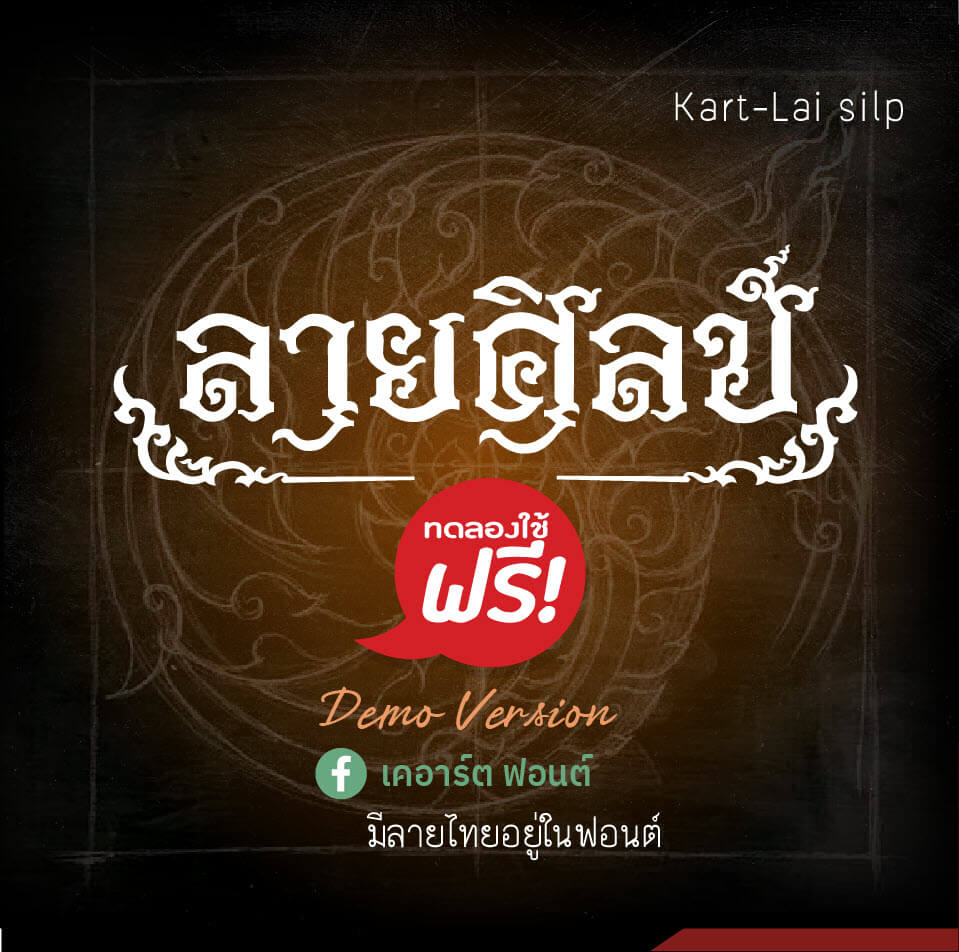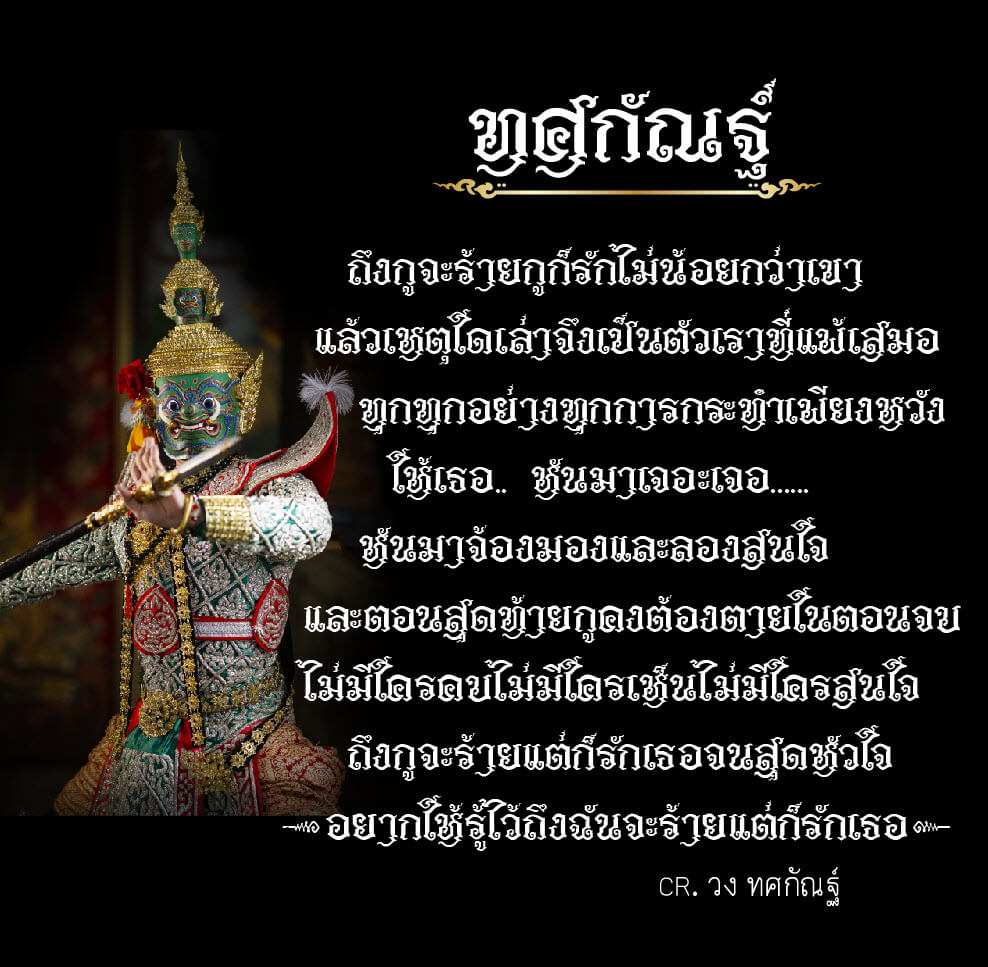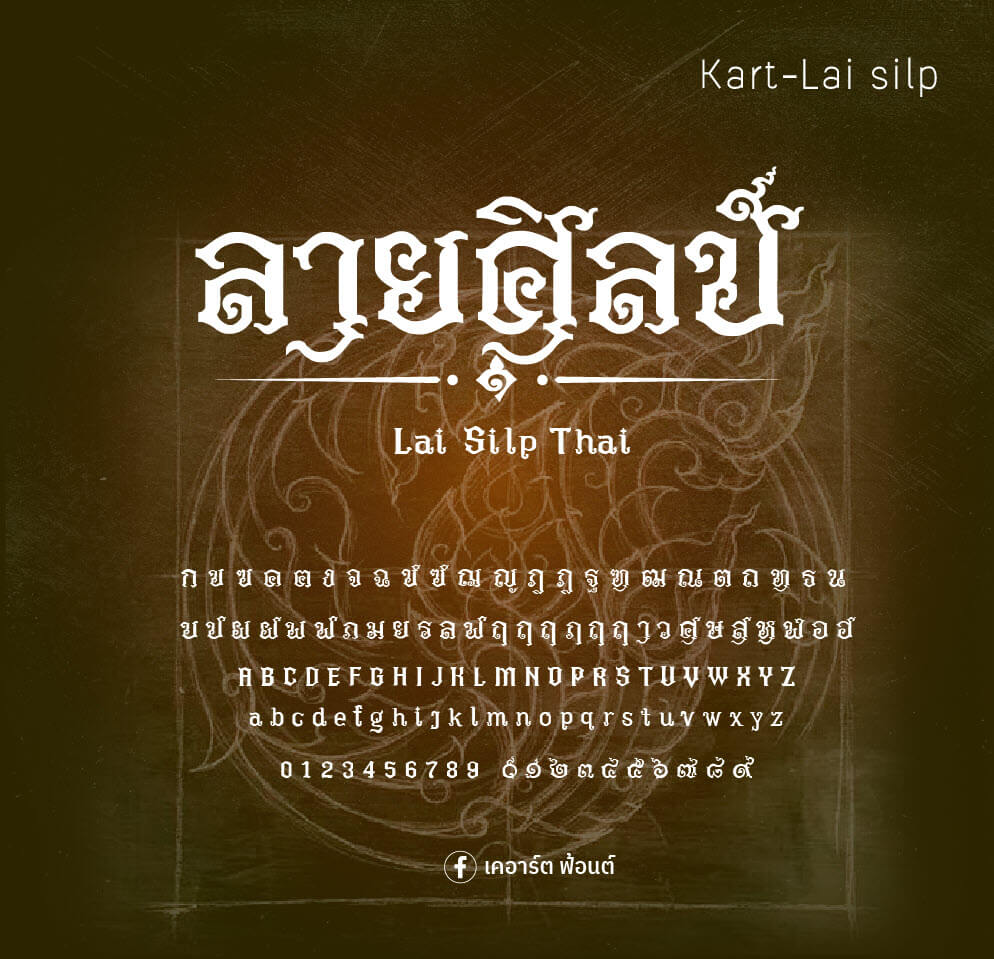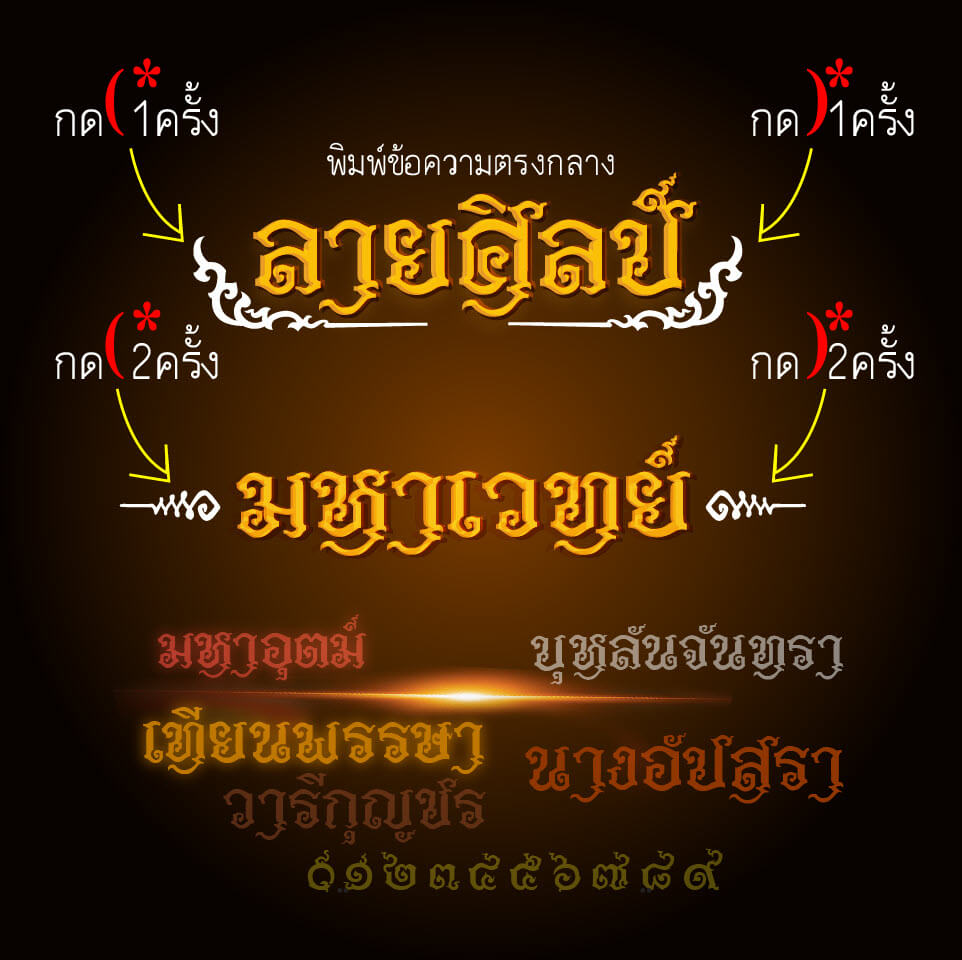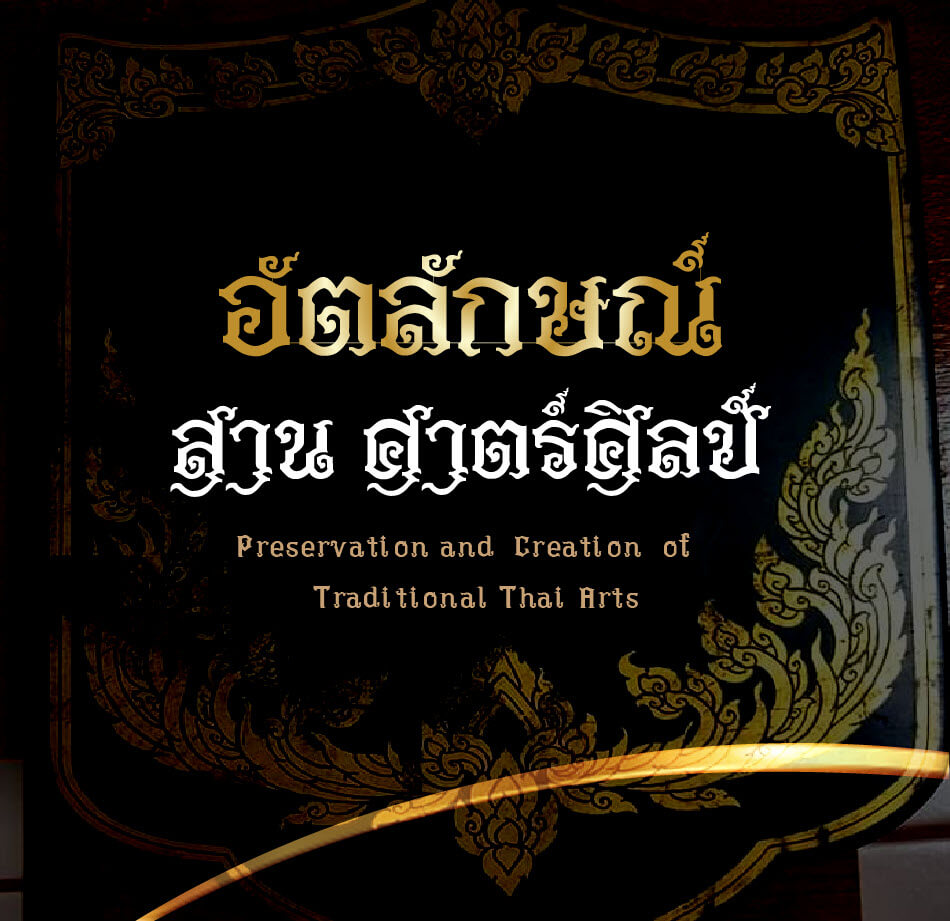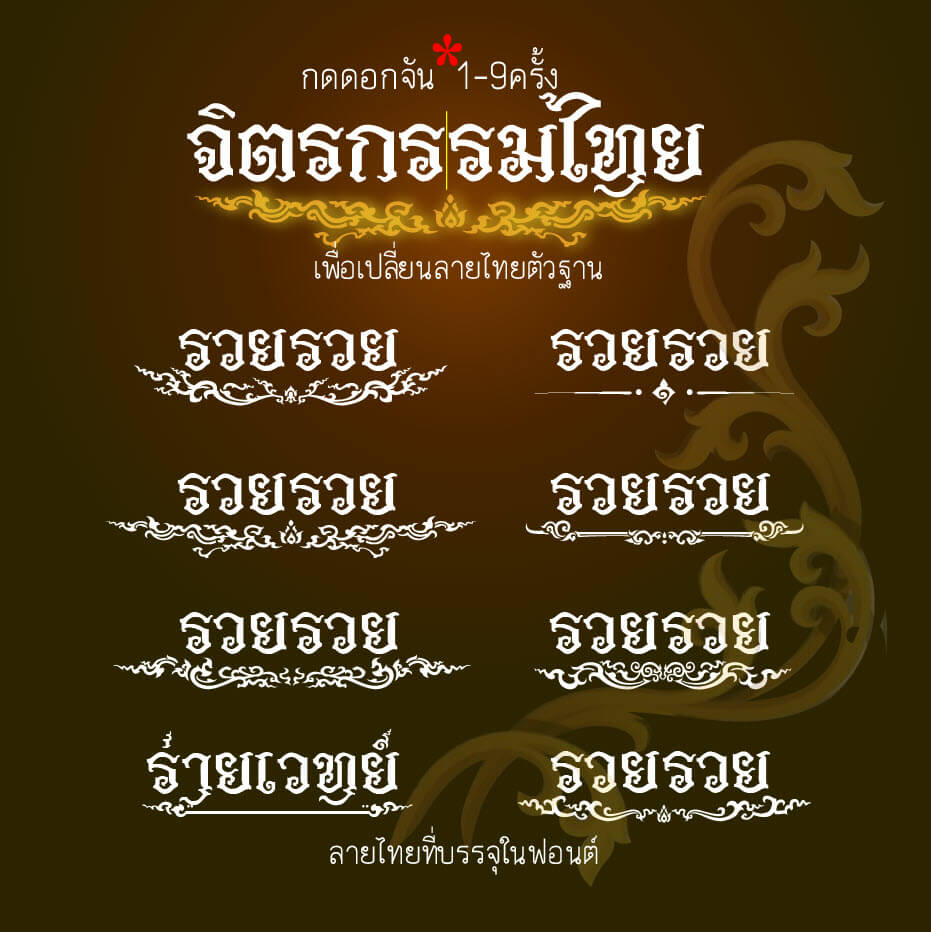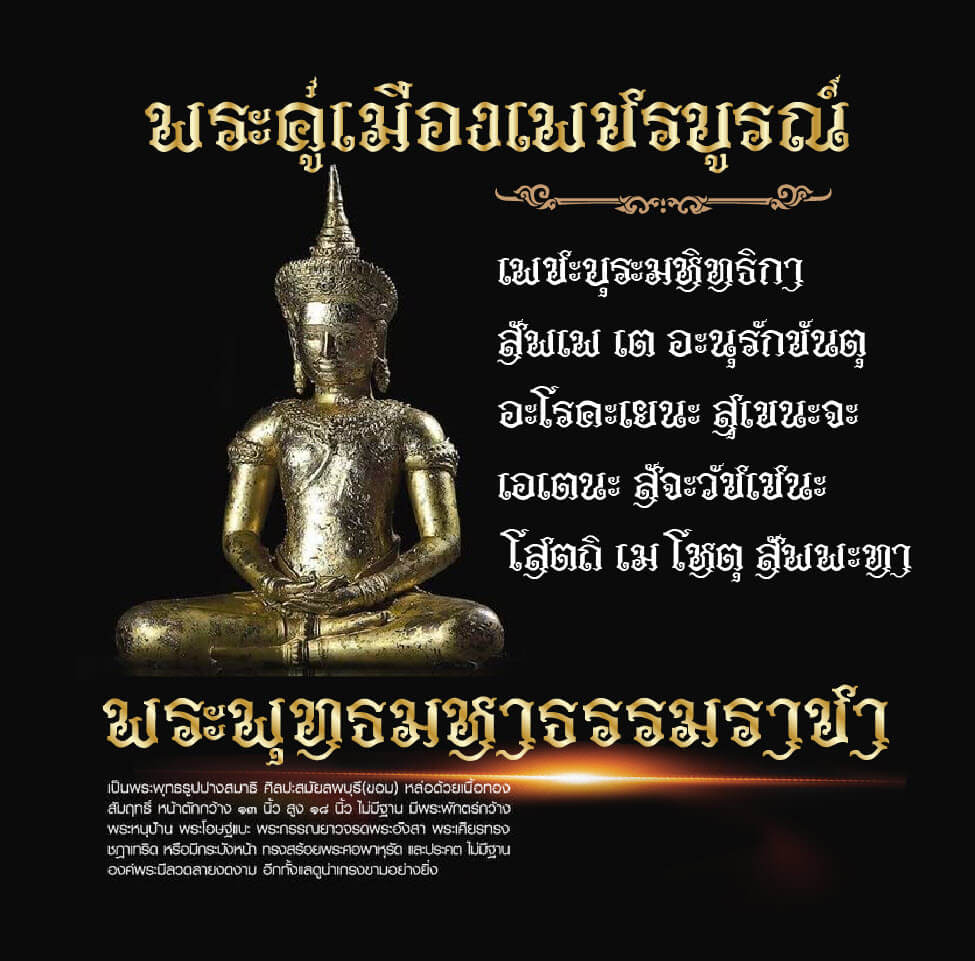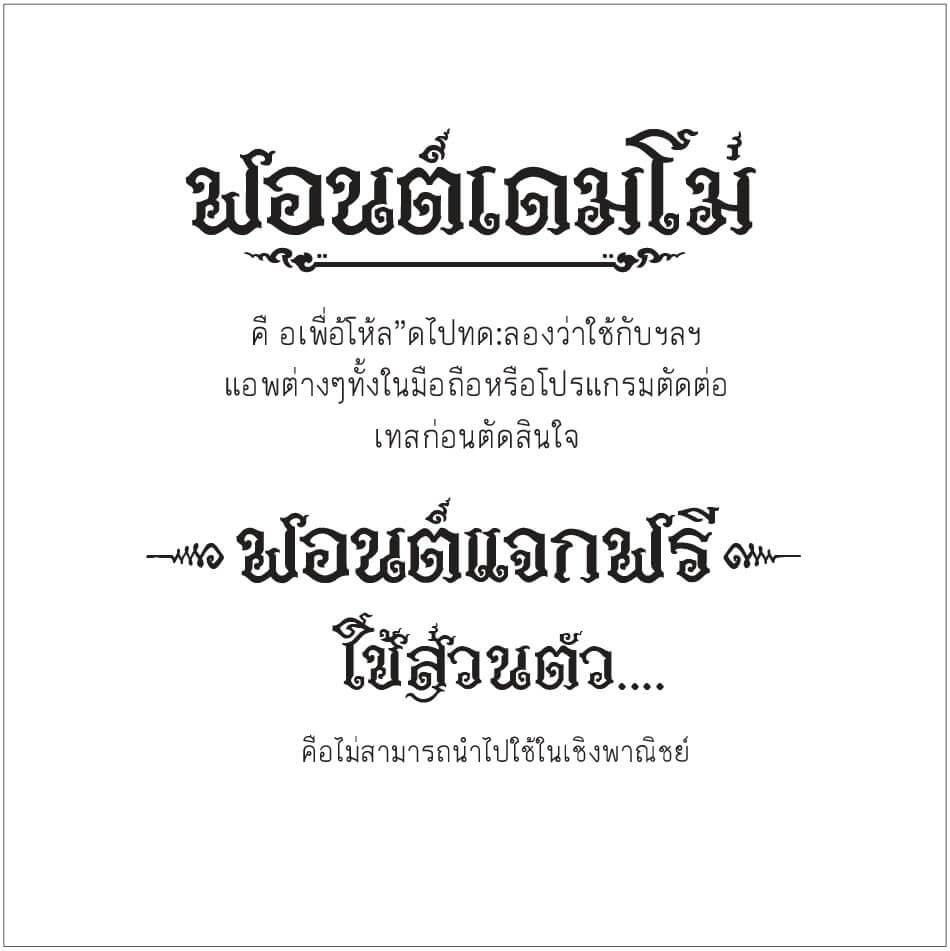
เคอาร์ต ลายศิลป์ (Kart-Lai silp) เป็นฟอนต์ที่อยากเขียนให้มีลายตัดไม่เน้นลายกนกแต่มีลายกนกในฟอนต์ โดยพิมพ์แล้วออกมาเป็นลายกนกเลย เน้นกลุ่มงานทั่วไปอยากให้ใช้ได้หลายประโยชน์